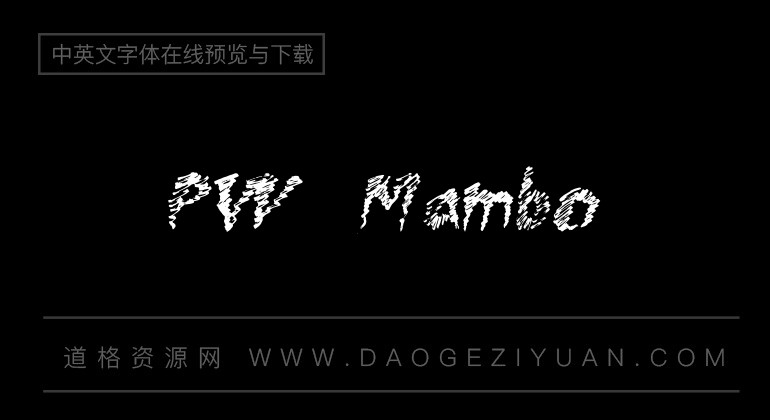
PW Mambo
PW Mambo是一款由比利时设计师Pieter van Rosmalen设计的新字体,它有着独特的风格,既有传统的活力,又有现代的活力,可以让文字更加引人注目。PW Mambo的字体比较宽,字形比较大,可以让文字更加显眼,令人印象深刻。此外,PW Mambo还具有良好的可读性,可以让文字更加清晰,让人们更容易理解文字的内容。
PW Mambo是一款非常不错的手写艺术字体,具有很好的视觉感,适合于文化类的宣传设计、商业类品牌的广告和产品包装设计以及个性化文字排版等较多场景。
PW Mambo字符映射图